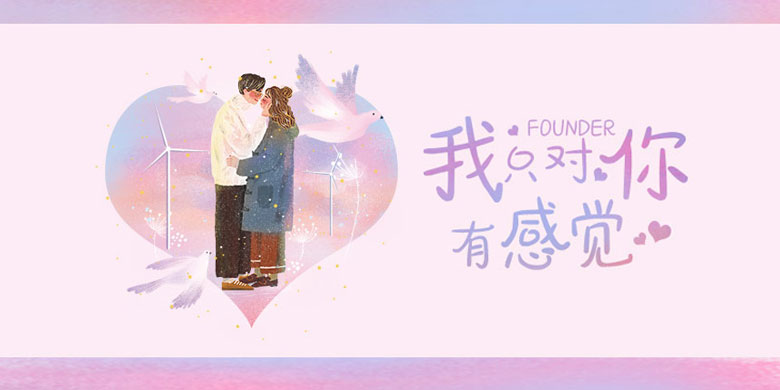
品牌:方正手迹设计师:尚正中发行时间:2020字库编码:大陆简体(GB2312-80)分类:创意书写字体属性:精品字
优秀的字体总能让人产生美好的意象。该字跳动的旋律感,及摇曳生姿的字形,宛如翩翩起舞的少女,自在随性,由内而外的欢喜。适用于文艺类的书刊、品牌广告和产品包装设计,以及社交网络的个性化用字。